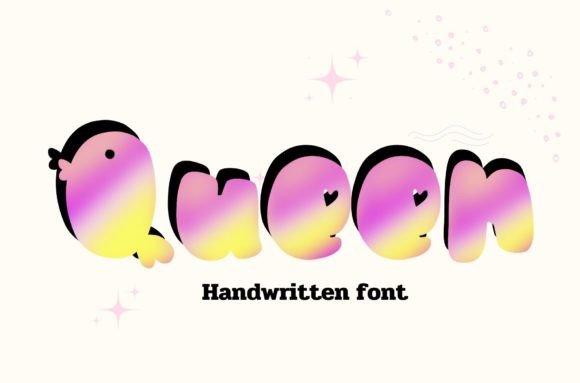
Queen
Jika Anda mencari aset berkualitas tinggi seperti Queen, paket premium ini adalah pilihan fantastis untuk proyek kreatif Anda.
Baik Anda membuat produk POD (Print on Demand), undangan pernikahan, atau grafis media sosial, Queen adalah pilihan yang sangat ideal.